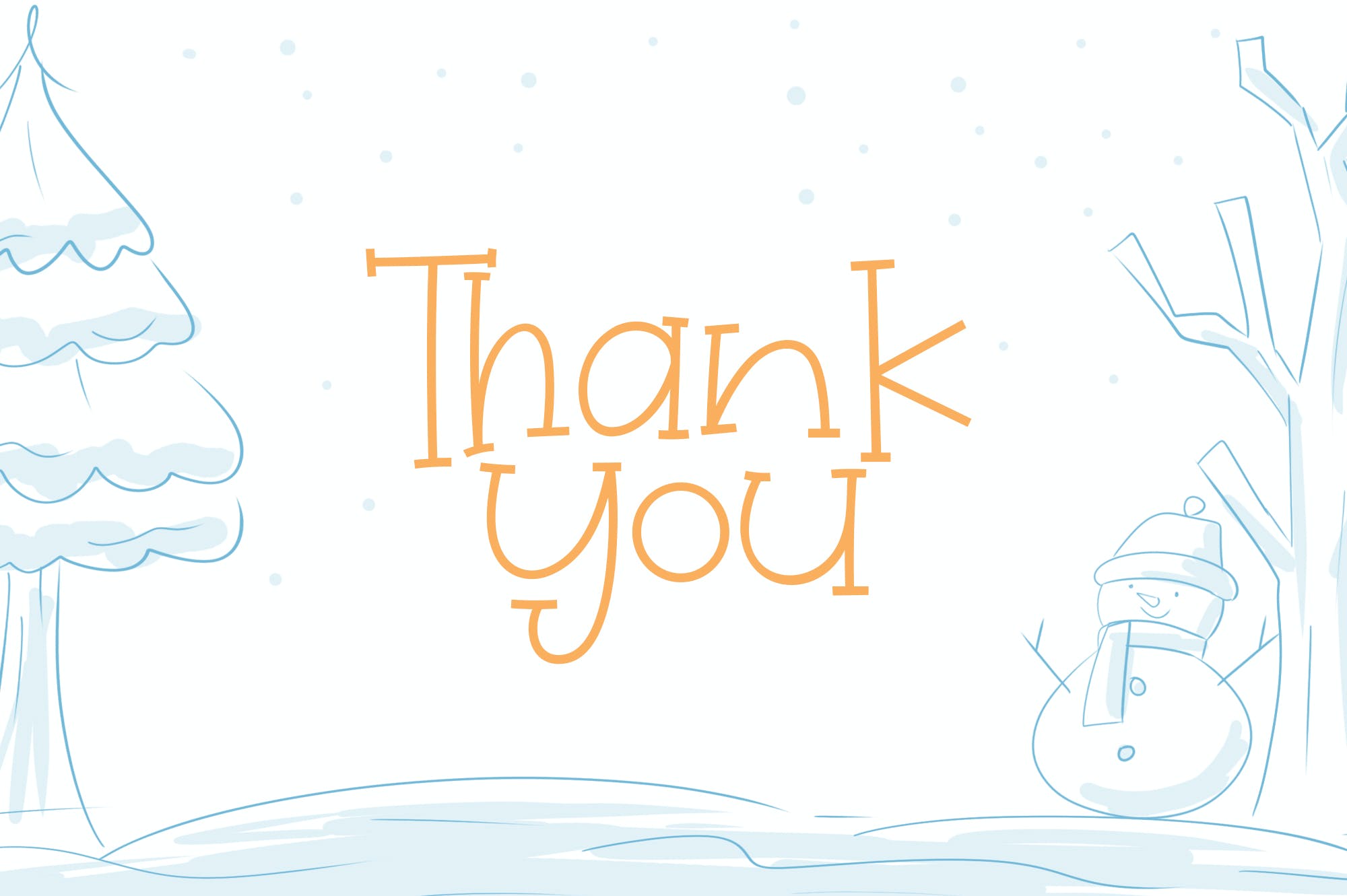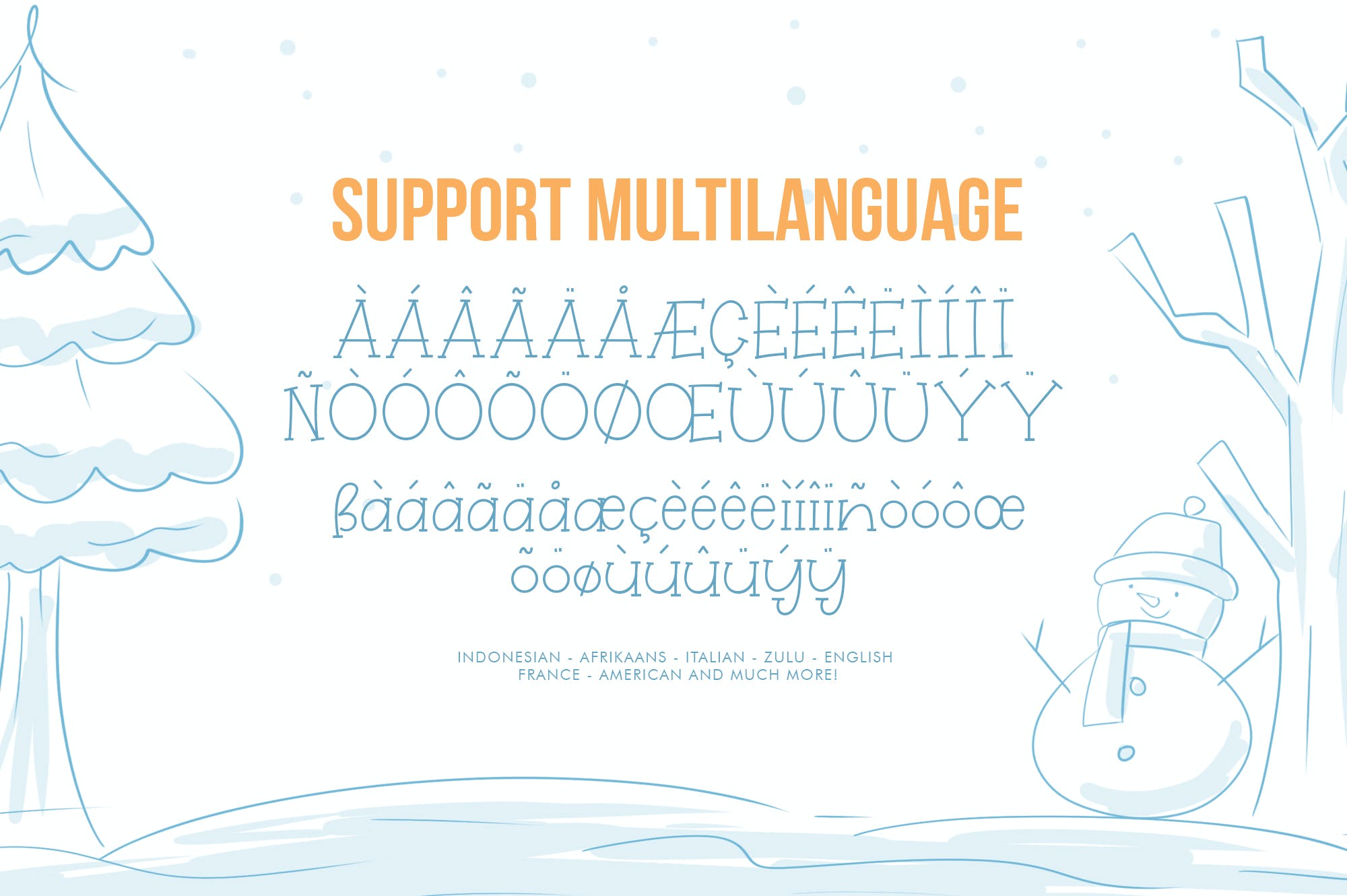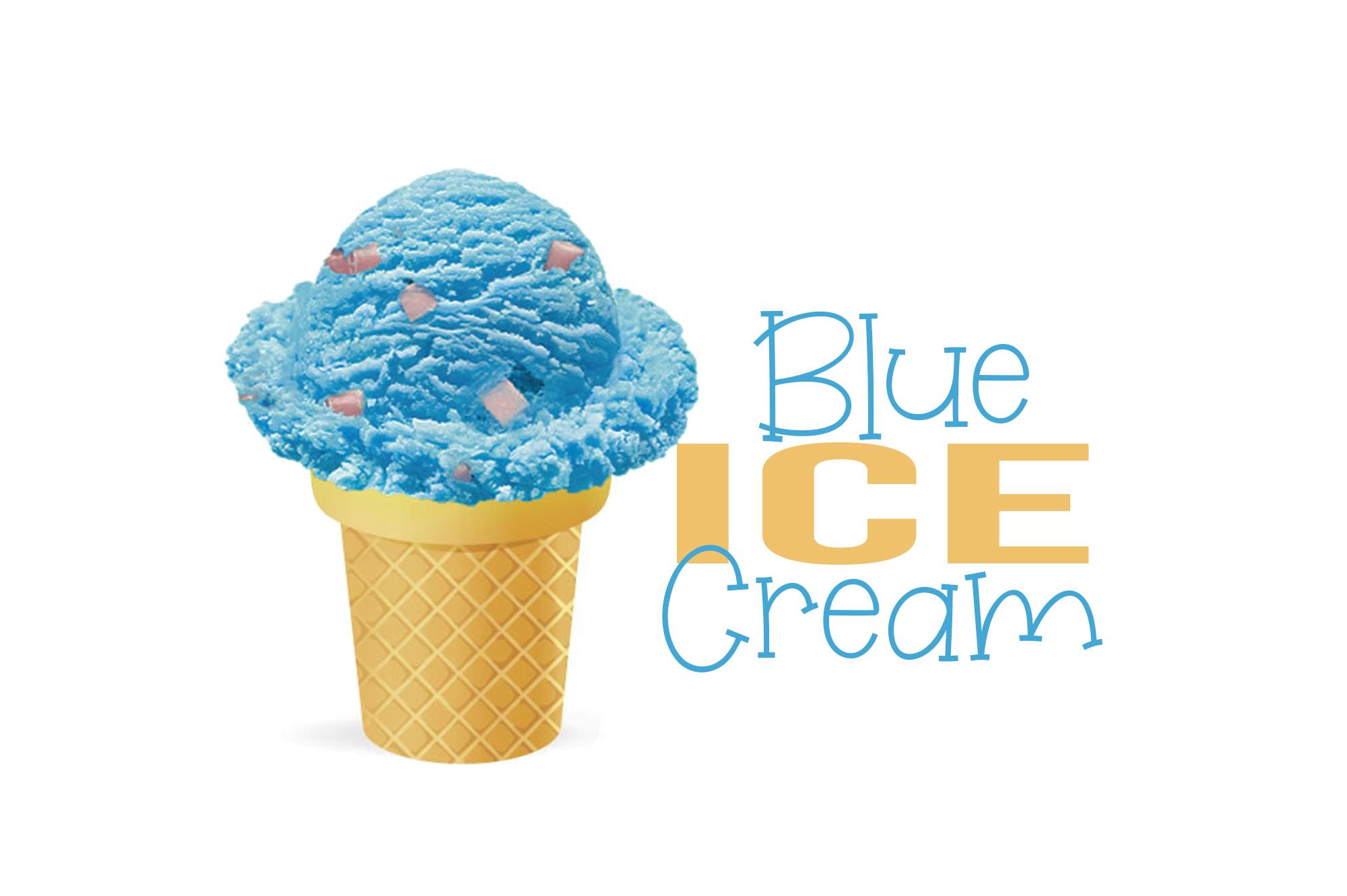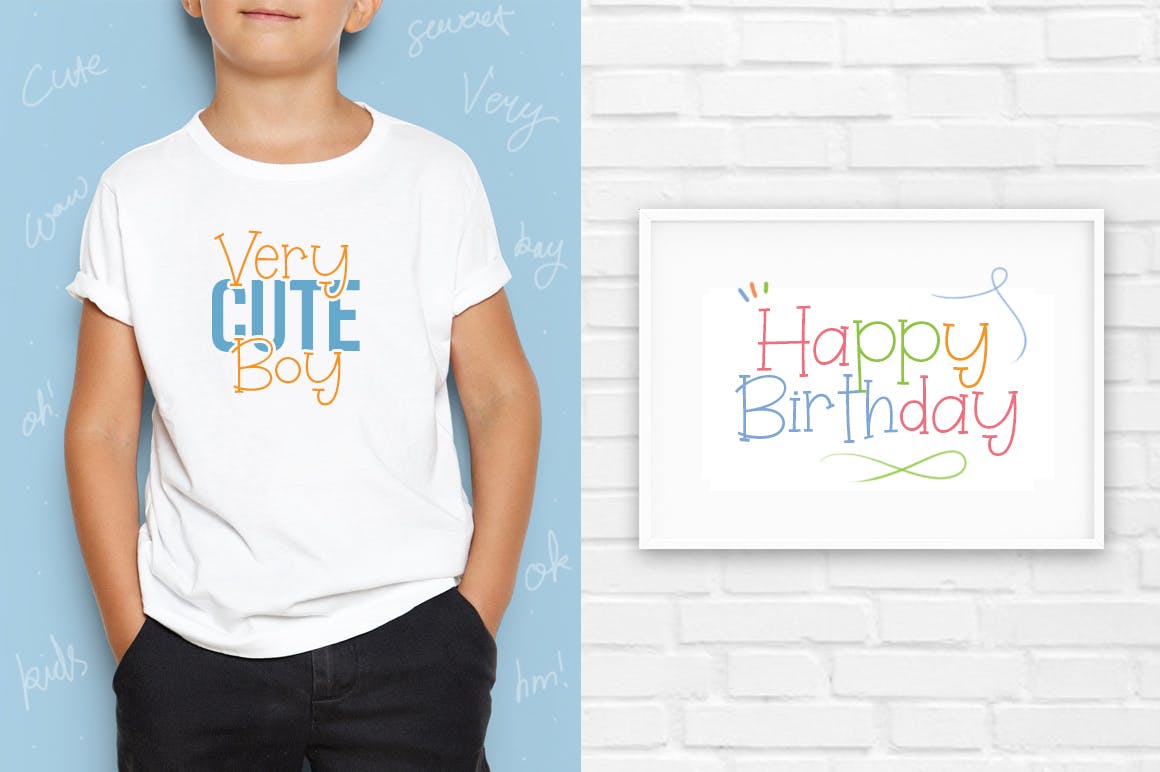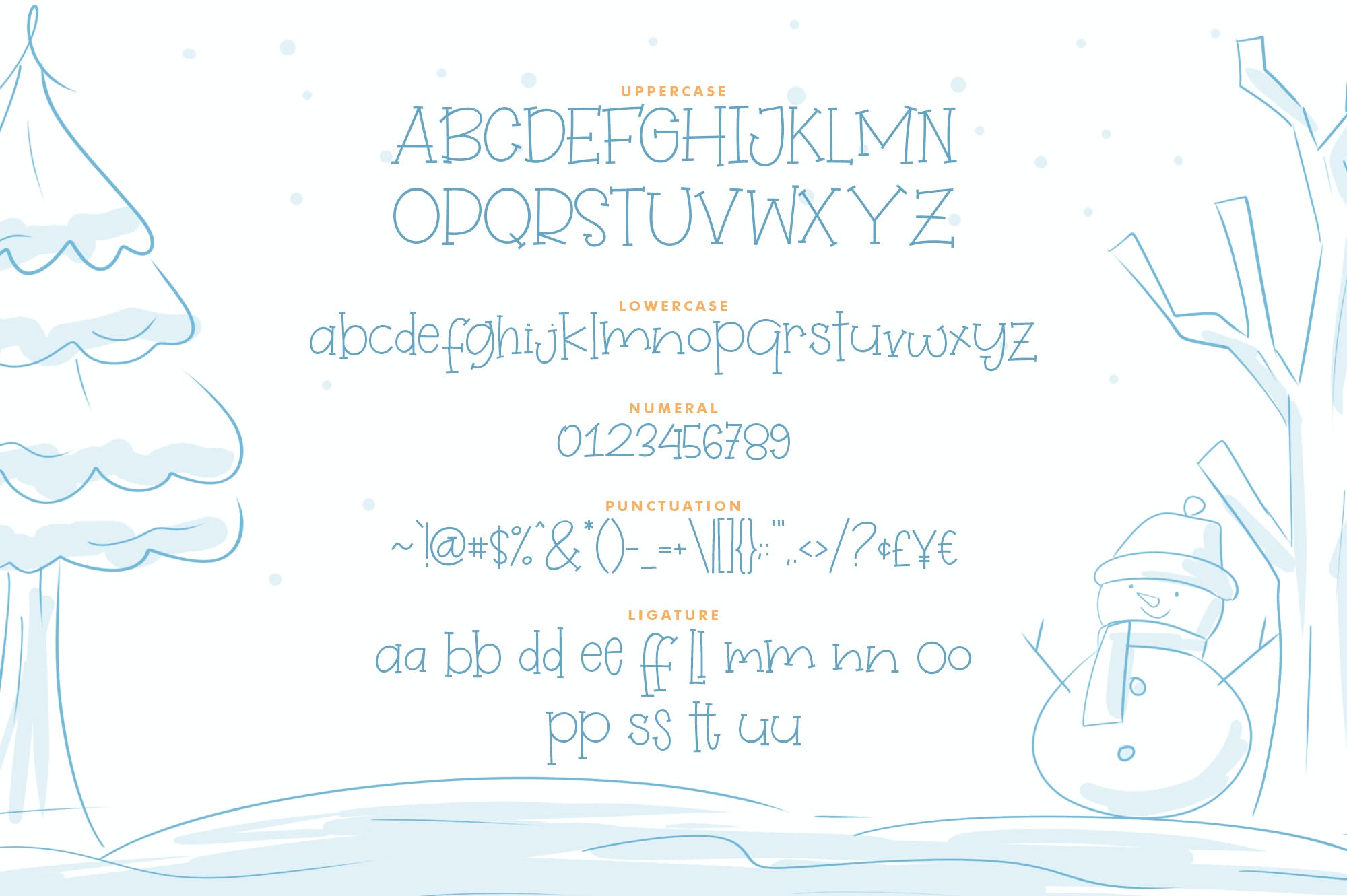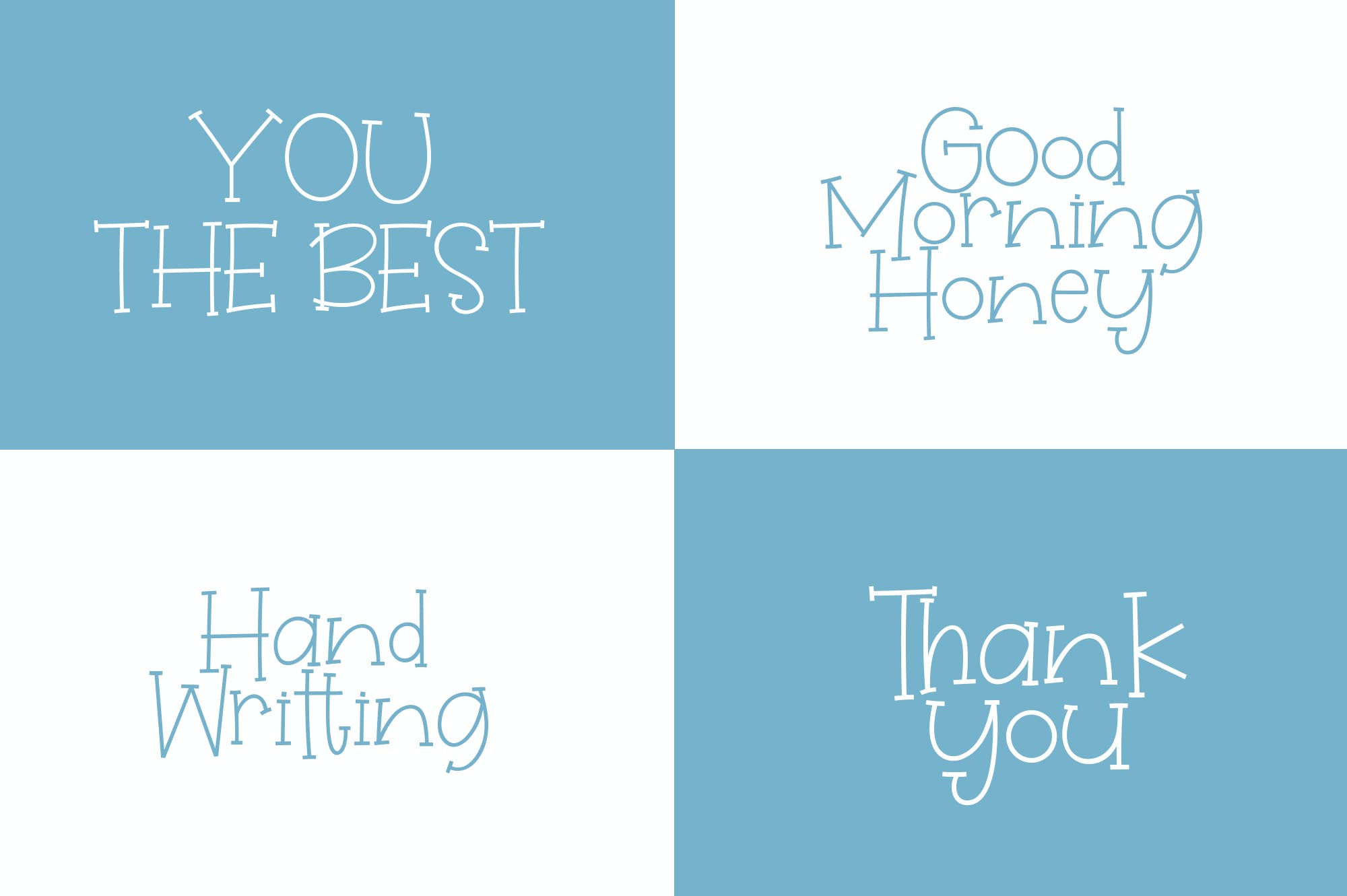
WinterLand Font
فونت WinterLand با دو سبک منحصر به فرد مناسب برای طراحی‌های شما.
فونت Winterland یک نوع فونت نمایشی با کاراکترهای جذاب و دو سبک مختلف، عادی و مایل است. این فونت برای طراحی‌هایی چون کارت ویزیت، پوستر، لوگو، مجله، جلد، بنر، تی‌شرت و سرعنوان‌ها و همچنین آثار هنری بزرگ مقیاس بسیار مناسب است.
ویژگی‌ها:
• ویژگی‌های OpenType
• حروف بزرگ و کوچک
• اعداد و نشانه‌گذاری
• کدگذاری PUA
• پشتیبانی چند زبانه